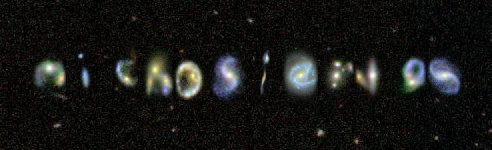
My Galaxies: una tipografía para escribir con galaxias «de verdad»
Curioso, ingenioso y simpático: My Galaxies utiliza imágenes de galaxias con apariencia de letras para escribir texto.
Y si el resultado no te gusta puedes pedir otra combinación de imágenes para el mismo texto.